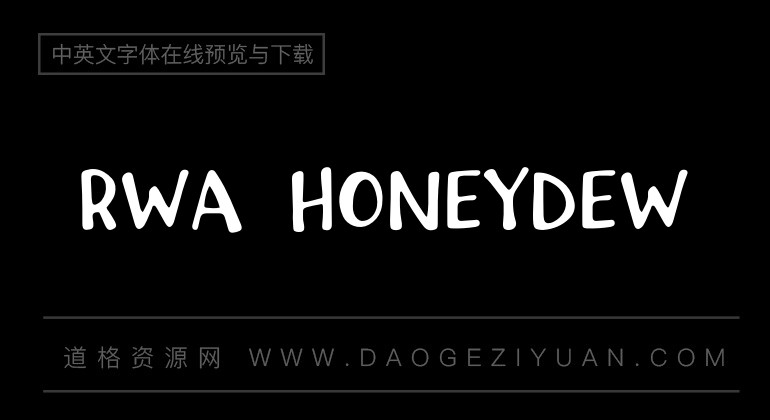
RWA Honeydew 是一款由 RWA 公司设计的艺术字体,它是一款漂亮而简洁的英文字体,适用于标题、标签和标语。RWA Honeydew 字体的特点是粗细的笔画和圆润的字体轮廓,给人以温柔、柔和、简约的感觉。RWA Honeydew 字体的字母和数字也比较优雅,具有良好的可读性,它可以提升文档的美感。内容介绍
RWA Honeydew是一款非常不错的手写艺术字体,具有很好的视觉感,适合于文化类的宣传设计、商业类品牌的广告和产品包装设计以及个性化文字排版等较多场景。